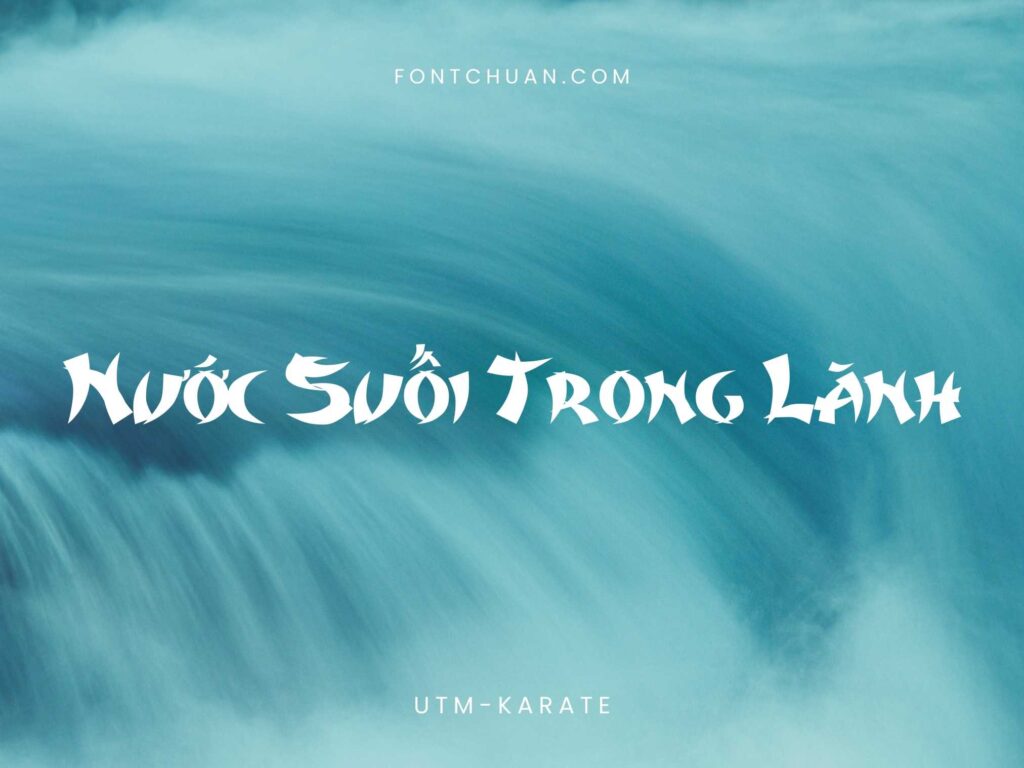
Font UTM Karate Việt Hóa
UTM Karate là một font chữ độc đáo mang phong cách võ thuật châu Á, được thiết kế với các đường nét mạnh mẽ và sắc sảo. Font này lấy cảm hứng từ các ký tự thư pháp phương Đông, tạo nên sự cá tính và đầy năng lượng trong thiết kế. Font đã được Việt hóa bởi Thiên Minh, hỗ trợ đầy đủ tiếng Việt cùng hơn 200 ngôn ngữ khác, giúp mở rộng khả năng sử dụng. Thành viên của Font Chuẩn đã sưu tầm và giới thiệu font này nhằm đáp ứng nhu cầu bạn đọc, cung cấp nguồn tham khảo chất lượng và ứng dụng thực tế vào các dự án thiết kế
Về đặc điểm thiết kế, UTM Karate có các đường nét góc cạnh, độ tương phản cao và kết hợp tinh thần Font Gothic với phong cách Font cổ trang, tạo cảm giác mạnh mẽ nhưng vẫn mang nét huyền bí. Font này phù hợp với nhiều ứng dụng như thiết kế tiêu đề, logo, poster, banner và các ấn phẩm sáng tạo khác. Các ngành nghề như quảng cáo, công nghệ, giáo dục và thiết kế thương hiệu có thể tận dụng font này để tạo nên sự khác biệt và thu hút trong các sản phẩm thiết kế.